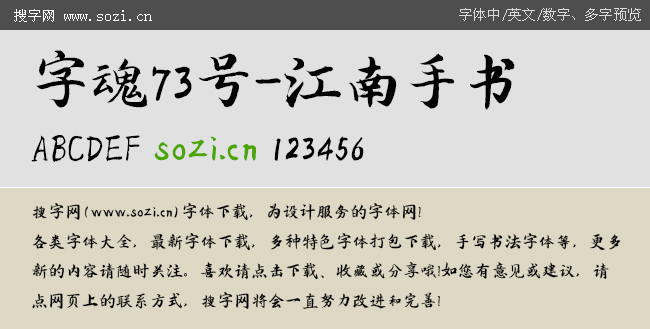
字魂73號-江南手書
搜字網(wǎng)提供一款字魂73號-江南手書中文字體下載,該字體是一款毛筆書法手寫字體,該字體包含6763個中文、字母、 符號和數(shù)字,具有優(yōu)雅、簡約、古典、婉約、手寫風 的風格,可以滿足您設(shè)計上的各種需求,該字體主要用于印刷品、屏顯、印章、企業(yè)店鋪、廣告、健康養(yǎng)生 等場景。